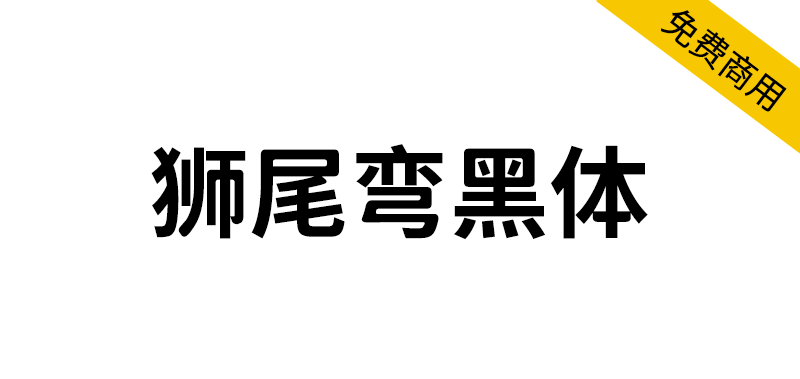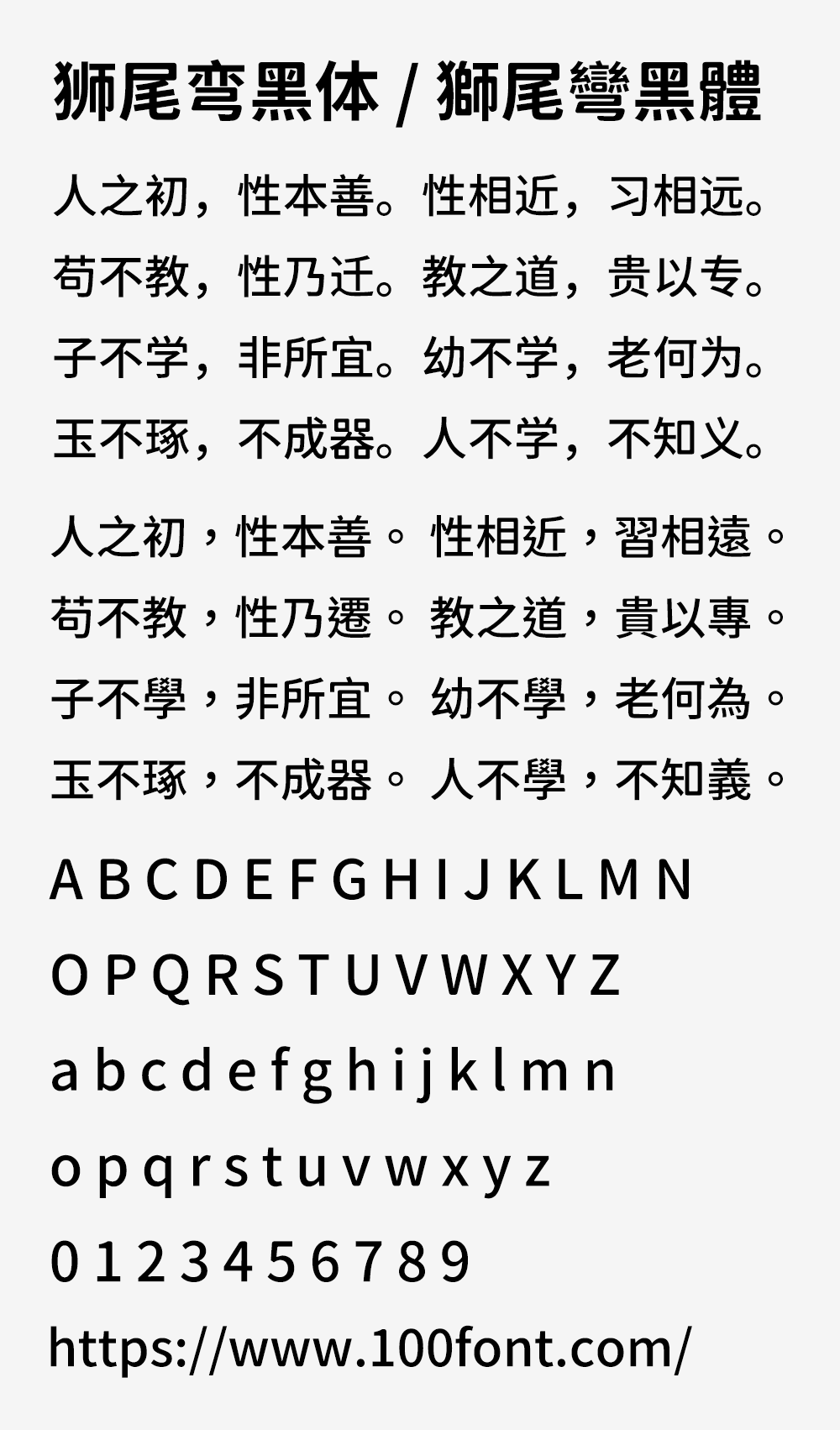
狮尾弯黑体基于思源黑体的变圆和拔脚改造,更加简明现代化的字体。和思源黑体一样,有7种字重。支持简体中文、繁体中文、韩文与日文,可以免费商用,欢迎大家自由应用、自由优化、自由改作!
狮尾弯黑体与「狮尾圆体」差别在笔触是否有做调整,狮尾弯黑体所套用的效果较少,在笔触没有做调整。
狮尾弯黑体与「狮尾弯腿黑体」差别在有没有拔脚,「拔脚」就是会有较少的笔画,例如移除「口」字的左右下角会多出的短线条。有拔脚的字会较圆,但是会造成有些字因直接去掉腿后左右不平衡、左右不对衬的「悬空」问题。改使用「腿」系列字体就不会有这个问题。